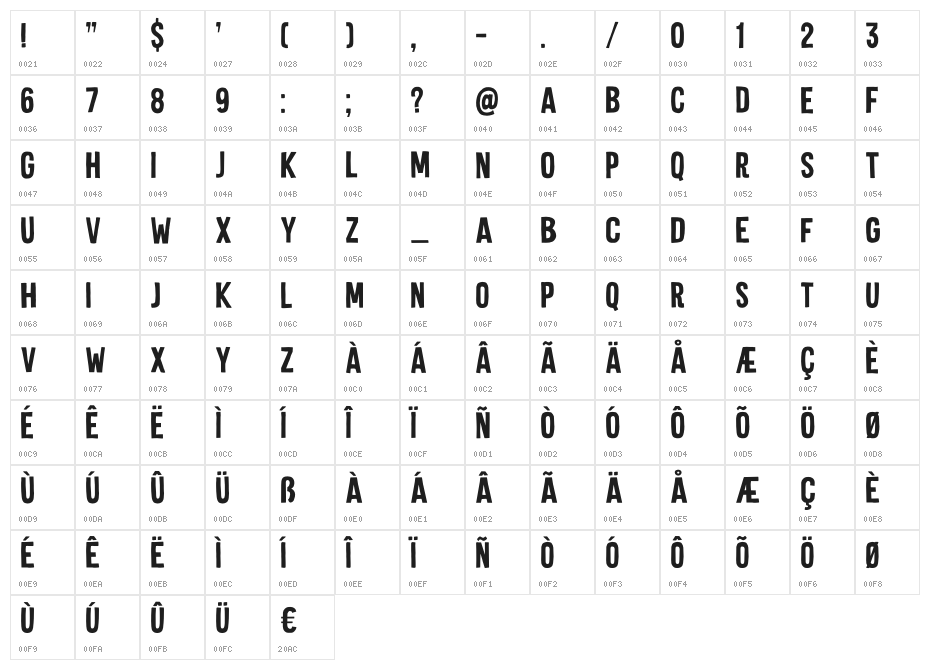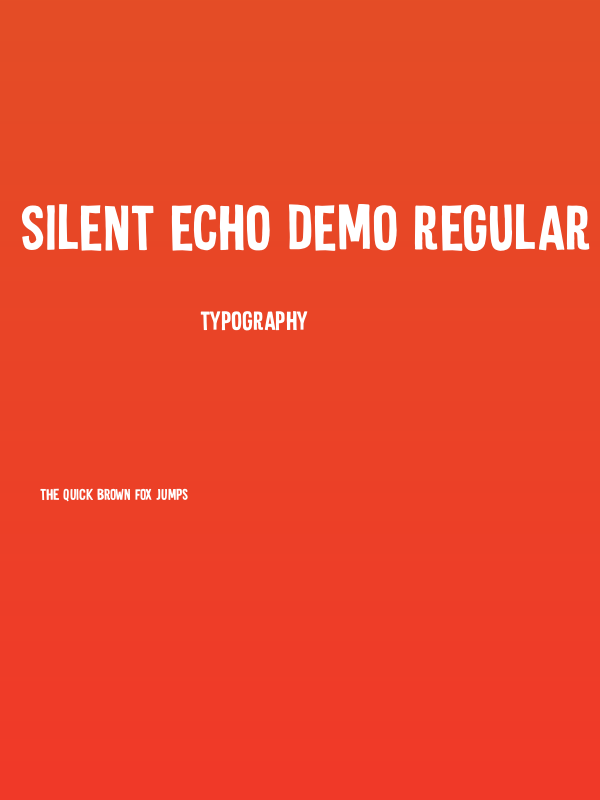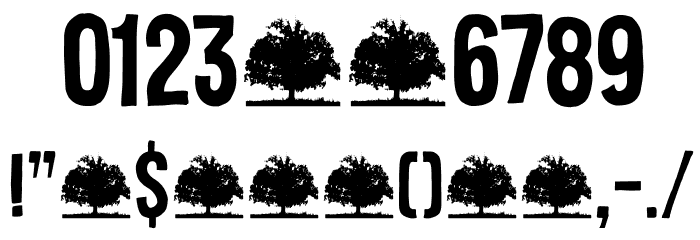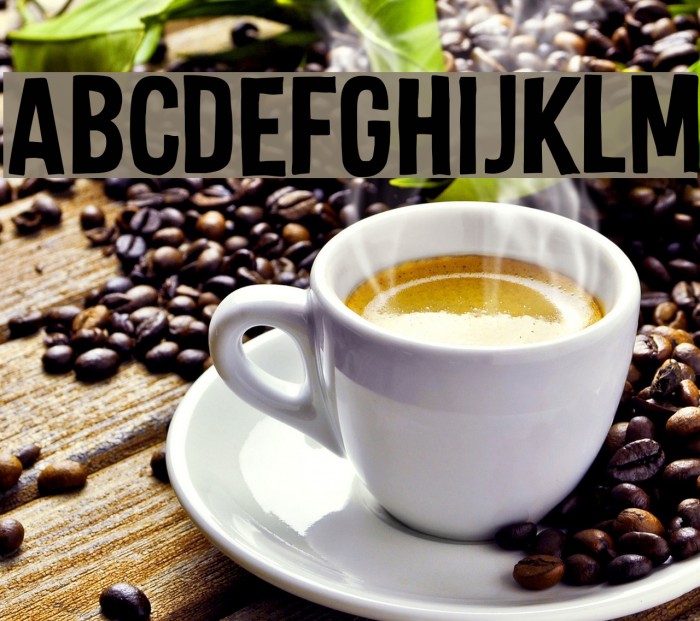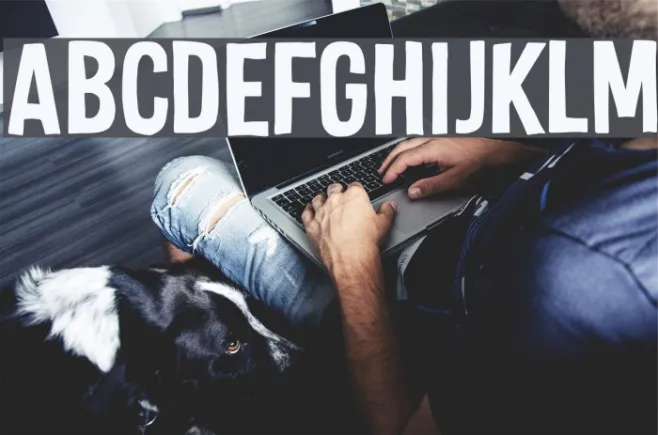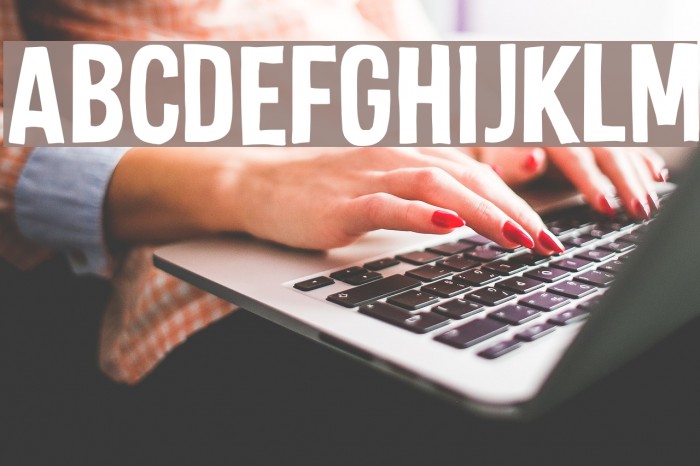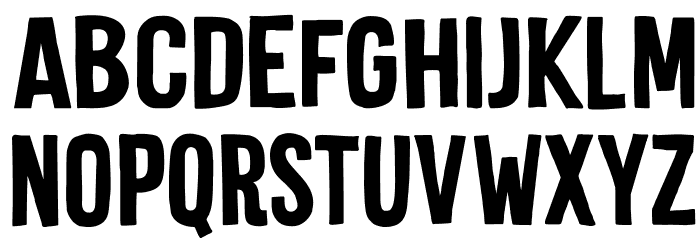
Silent Echo DEMO Regular Font
| Estilo general | Rustic, Organic |
| Proyectos propuestos | Ideal for nature-themed branding, outdoor event posters, eco-friendly product packaging, and rustic signage. |